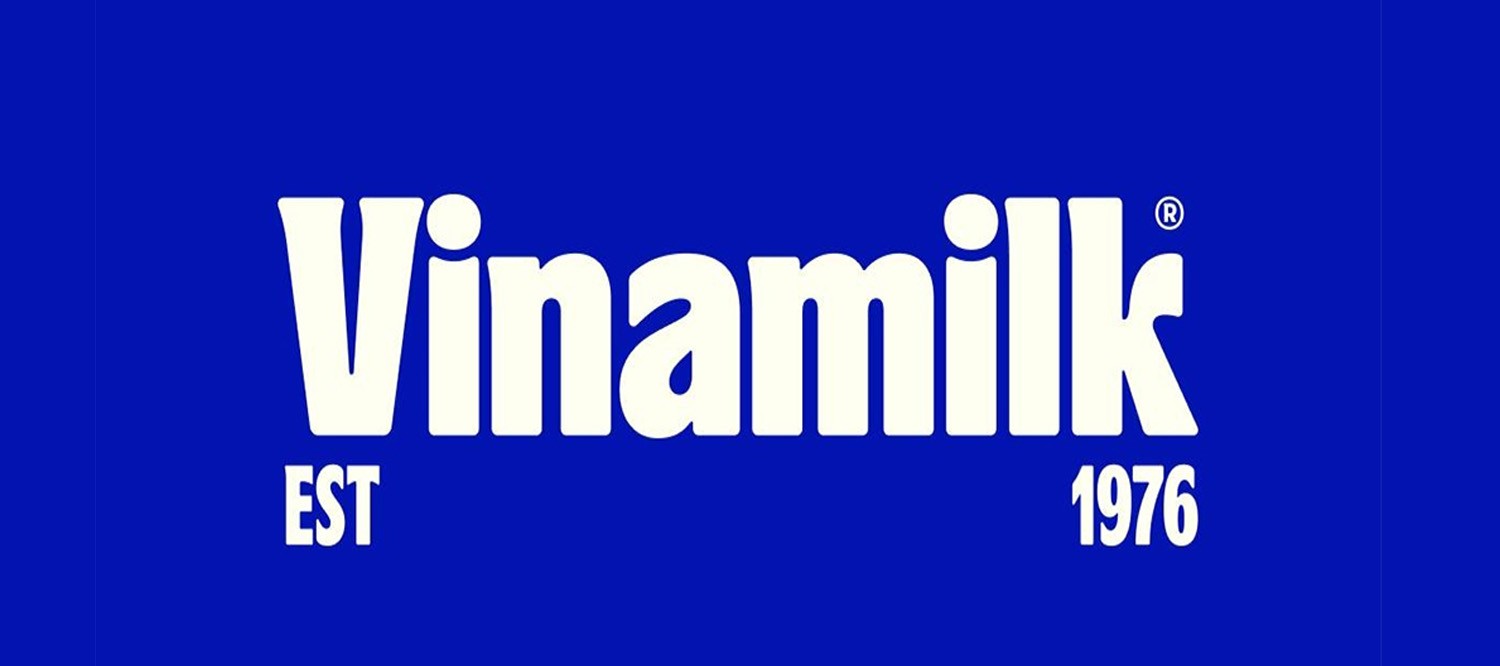
Giới Thiệu Font Chữ VNM Sans Display: Bộ Nhận Diện Thương Hiệu Mới Của Vinamilk
Vinamilk, một trong những thương hiệu sữa hàng đầu tại Việt Nam, đã không ngừng đổi mới và phát triển để duy trì vị thế của mình trên thị trường. Gần đây, thương hiệu này đã cho ra mắt logo mới cùng bộ nhận diện thương hiệu được làm mới toàn diện, trong đó, font chữ VNM Sans Display đóng vai trò quan trọng trong việc thể hiện hình ảnh thương hiệu mới.
Font Chữ VNM Sans Display Là Gì?
VNM Sans Display là font chữ mới được Vinamilk phát triển và sử dụng trong bộ nhận diện thương hiệu mới của mình. Font chữ này được thiết kế đặc biệt để phù hợp với các giá trị cốt lõi của Vinamilk: chuyên nghiệp, hiện đại và gần gũi với người tiêu dùng. Sự ra đời của VNM Sans Display đánh dấu một bước tiến mới trong chiến lược xây dựng và phát triển thương hiệu của Vinamilk, giúp thương hiệu này trở nên nổi bật và dễ nhận diện hơn trong mắt người tiêu dùng.
Đặc Điểm Của Font Chữ VNM Sans Display
Phong Cách Hiện Đại
VNM Sans Display mang phong cách hiện đại với các đường nét rõ ràng, mạch lạc và cân đối. Font chữ này thể hiện sự đơn giản nhưng không kém phần tinh tế, phù hợp với xu hướng thiết kế hiện đại và mang lại cảm giác thân thiện cho người xem.
Tính Chuyên Nghiệp Cao
Font chữ VNM Sans Display được thiết kế để truyền tải tính chuyên nghiệp, phản ánh đúng tinh thần và giá trị của Vinamilk. Các đường nét sắc sảo và cấu trúc rõ ràng của font chữ giúp tạo nên một hình ảnh đáng tin cậy và uy tín, điều này đặc biệt quan trọng đối với một thương hiệu lớn trong ngành thực phẩm và đồ uống như Vinamilk.
Sự Đa Dụng Trong Ứng Dụng
VNM Sans Display không chỉ được sử dụng trong logo mà còn trong nhiều hạng mục khác của bộ nhận diện thương hiệu như bao bì sản phẩm, tài liệu quảng cáo, website và các phương tiện truyền thông. Tính đa dụng của font chữ này giúp Vinamilk dễ dàng duy trì sự nhất quán trong hình ảnh thương hiệu trên tất cả các kênh truyền thông và điểm tiếp xúc với khách hàng.
Dễ Nhận Diện và Gợi Nhớ
Một trong những ưu điểm nổi bật của VNM Sans Display là khả năng nhận diện và gợi nhớ cao. Font chữ này được thiết kế với độ tương phản tốt, giúp chữ dễ đọc và nổi bật trên nhiều nền khác nhau. Điều này không chỉ giúp logo của Vinamilk trở nên rõ ràng hơn mà còn giúp thương hiệu ghi dấu ấn mạnh mẽ trong tâm trí người tiêu dùng.
Tại Sao Vinamilk Chọn VNM Sans Display?
Phản Ánh Giá Trị Cốt Lõi Của Thương Hiệu
Vinamilk là một thương hiệu lâu đời và uy tín trong ngành thực phẩm và đồ uống, đặc biệt là các sản phẩm từ sữa. Việc lựa chọn VNM Sans Display giúp Vinamilk thể hiện rõ ràng các giá trị cốt lõi của mình: chất lượng, sự tin cậy và sự gần gũi với người tiêu dùng. Font chữ này mang lại cảm giác thân thiện, dễ tiếp cận nhưng vẫn duy trì được tính chuyên nghiệp, rất phù hợp với hình ảnh mà Vinamilk muốn xây dựng.
Hỗ Trợ Cho Chiến Lược Phát Triển Thương Hiệu
Vinamilk không chỉ tập trung vào chất lượng sản phẩm mà còn chú trọng đến việc xây dựng và phát triển thương hiệu. Việc sử dụng VNM Sans Display trong bộ nhận diện thương hiệu mới là một phần quan trọng trong chiến lược này. Font chữ hiện đại và dễ nhận diện này giúp Vinamilk củng cố vị thế của mình trên thị trường, đồng thời mở ra cơ hội tiếp cận với nhiều đối tượng khách hàng hơn.
Khả Năng Thích Ứng Cao
VNM Sans Display được thiết kế với mục đích sử dụng rộng rãi trên nhiều nền tảng và kênh truyền thông khác nhau. Từ các sản phẩm in ấn như bao bì, tờ rơi đến các nền tảng kỹ thuật số như website, ứng dụng di động, font chữ này đều có khả năng thích ứng tốt, đảm bảo rằng hình ảnh thương hiệu Vinamilk luôn nhất quán và chuyên nghiệp.
Ứng Dụng Của VNM Sans Display Trong Bộ Nhận Diện Thương Hiệu Vinamilk
Logo Và Bao Bì Sản Phẩm
Logo mới của Vinamilk là nơi mà VNM Sans Display được sử dụng rõ ràng và hiệu quả nhất. Font chữ này không chỉ giúp logo trở nên hiện đại và chuyên nghiệp hơn mà còn giúp tăng cường sự nhận diện thương hiệu. Trên các bao bì sản phẩm, VNM Sans Display giúp tạo ra sự đồng nhất về hình ảnh, từ các sản phẩm sữa tươi, sữa chua đến các loại nước uống dinh dưỡng khác.
Tài Liệu Quảng Cáo và Marketing
Trong các tài liệu quảng cáo và marketing, VNM Sans Display giúp Vinamilk truyền tải thông điệp một cách rõ ràng và thu hút. Các brochure, tờ rơi, poster sử dụng font chữ này không chỉ bắt mắt mà còn mang lại cảm giác tin cậy, thuyết phục người tiêu dùng về chất lượng của sản phẩm Vinamilk.
Website Và Truyền Thông Số
Trên các nền tảng số, VNM Sans Display đảm bảo rằng mọi thông tin từ Vinamilk đều được truyền tải một cách rõ ràng và nhất quán. Website của Vinamilk, các trang mạng xã hội, và các chiến dịch quảng cáo trực tuyến đều sử dụng font chữ này để tạo nên một hình ảnh chuyên nghiệp và đồng bộ.
Việc sử dụng VNM Sans Display là một bước tiến chiến lược của Vinamilk trong việc củng cố vị thế thương hiệu, tăng cường sự gắn kết với khách hàng và mở rộng thị trường. Đây là minh chứng rõ ràng cho sự cam kết của Vinamilk trong việc không ngừng đổi mới và phát triển để mang lại những giá trị tốt nhất cho người tiêu dùng.